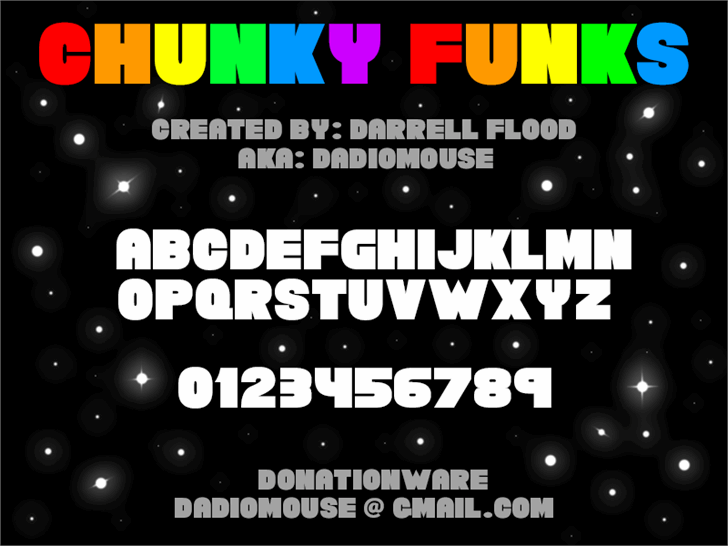
A fonte “Chunky Funks” surge diretamente do universo criativo de High Logic FontCreator, desenvolvida pelo talentoso designer Darrell Flood. Inspirada na dinâmica e energia vibrante dos anos 80, essa sans serif é uma explosão em cores vivas que se torna perfeitamente adaptável para qualquer projeto visual. Com linhas grossas e um toque de personalidade, “Chunky Funks” carrega consigo o encanto desse estilo único que não hesita em chamar atenção onde quer que caia. Ideal tanto para design gráfico pessoal quanto para uma ampla gama de aplicativos digitais, esta fonte é a escolha perfeita para aqueles buscando um contraste vibrante e elegante no seu próximo projeto. É gratuita para uso pessoal, embora um gesto de apoio seja sempre bem vindo se o design for usado de maneira mais ampla.